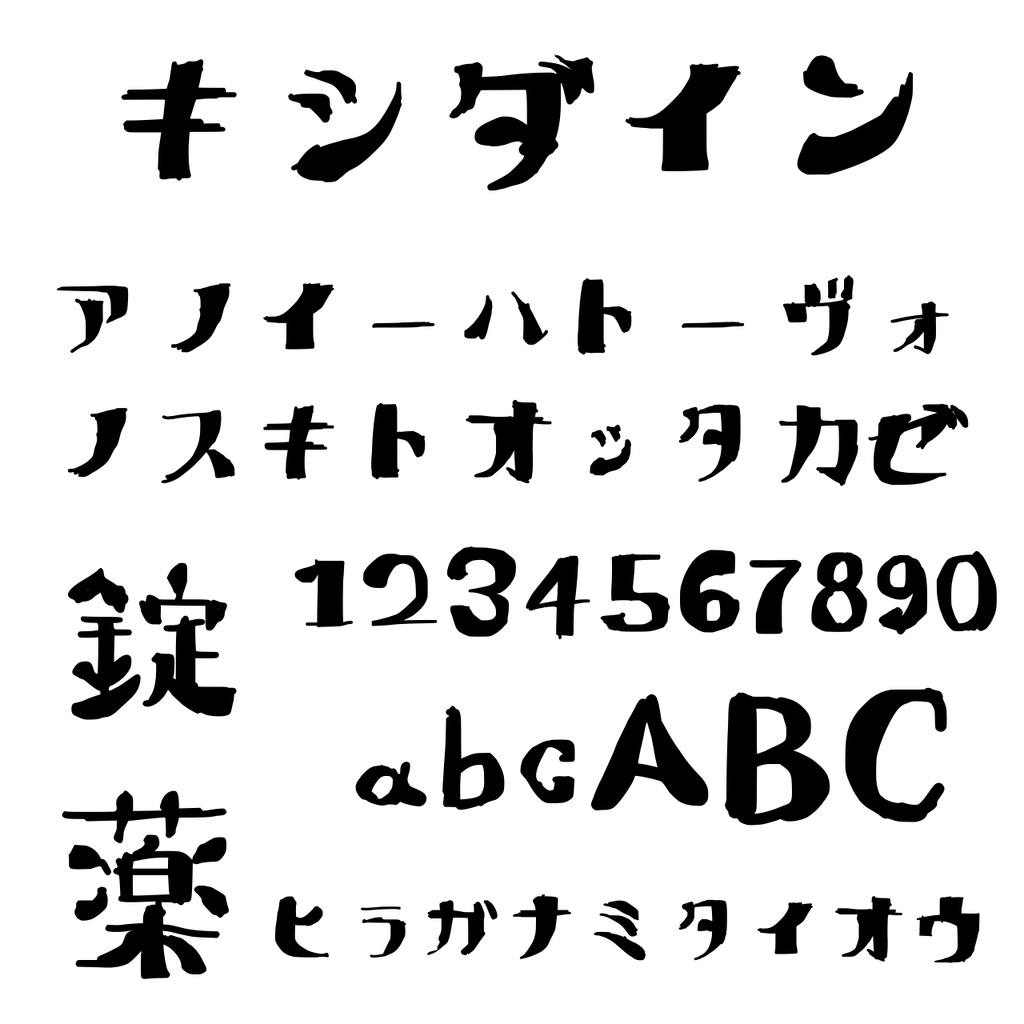
風野農園直売所自作フリーフォント 『キシダイン』ダウンロード商品¥ 0無料ダウンロードxydyne100mg.zip (70.1 KB)xydyne100mg.zip「ギフトとして贈る」とは薬のシートとかに書かれているようなフォントです。 キレイな線ではなく、あえてガサガサした手書きの線になってます。 ずっと無料で配布する予定です。 ひらがなは未対応です。漢字は「薬」「錠」のみ使えます。 あとは自由につかってください。 商用利用の際は声をかけてください。風野農園直売所FANBOX開設中